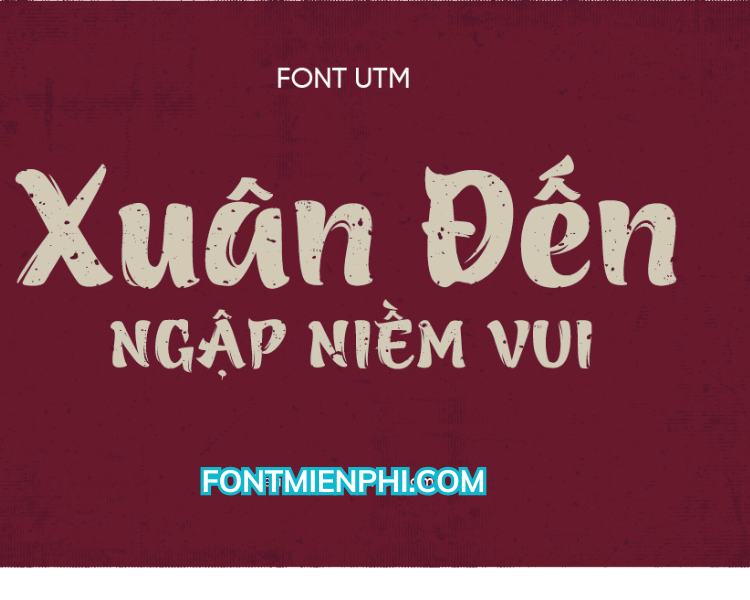
Việt hóa font UTM Azuki ,font Tết
Font UTM Azuki là một kiểu chữ Việt hóa, thường được sử dụng trong các thiết kế mang tính nghệ thuật và truyền thống. Đây là một font chữ mang đậm phong cách hiện đại nhưng vẫn giữ được nét đẹp cổ điển, phù hợp cho các sản phẩm truyền thông, quảng cáo, đặc biệt là trong dịp Tết Nguyên Đán.
Đặc điểm nổi bật của font UTM Azuki:
• Thiết kế độc đáo: Font chữ có những đường nét mềm mại, uyển chuyển, tạo cảm giác ấm áp và gần gũi.
• Sự kết hợp giữa hiện đại và truyền thống: UTM Azuki không chỉ phù hợp với các thiết kế hiện đại mà còn hòa quyện tốt với các yếu tố văn hóa truyền thống của người Việt.
• Tính ứng dụng cao: Có thể được sử dụng trong nhiều loại hình thiết kế như thiệp chúc Tết, banner quảng cáo, hoặc các sản phẩm văn hóa khác.
Sử dụng:
Font UTM Azuki thích hợp cho việc in ấn và thiết kế số, giúp tạo nên một không gian Tết vui tươi và đầy màu sắc. Việc sử dụng font chữ này trong các sản phẩm liên quan đến Tết sẽ góp phần tạo nên không khí lễ hội và sự phấn khởi cho người dùng.